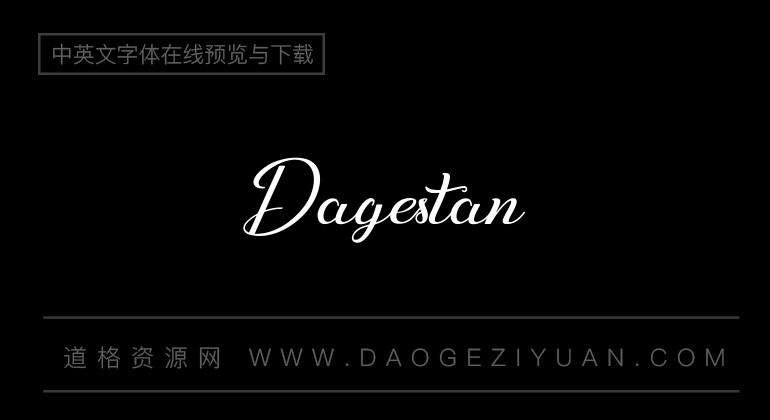
Dagestan
Dagestan 字体是一种由俄罗斯设计师 Nadezhda Polomoshnova 创作的英文字体。它的特点是有大量的花纹装饰,字体的细节表现出了东方风格的精致和细腻。它有着鲜明的设计风格,能够带来视觉上的冲击,可以让文字更有表现力。Dagestan 字体可以用于各种类型的设计项目,如标志设计,海报设计,书籍封面,电影海报,海报,报纸,杂志,网页设计,品牌标识等。
Dagestan是一款非常不错的手写艺术字体,具有很好的视觉感,适合于文化类的宣传设计、商业类品牌的广告和产品包装设计以及个性化文字排版等较多场景。